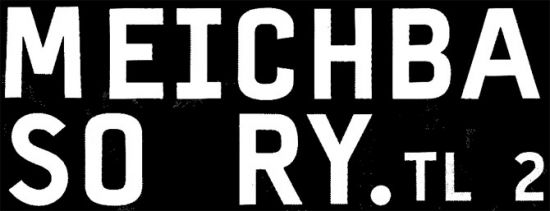
TELE2 Corporate Design Font
hallo zusammen. heute habe ich eine TELE2-Anzeige mit beiliegenden Zeichen gesehen. weiss jemand, welche Schrift die verwenden? (Man beachte die Enden beim "C", die Kurvenform beim "O", die leichte Neigung der "M"-Abstriche sowie das Bein des "R"). Besten Dank und Herzliche Grüsse2476_tele2_1.jpg